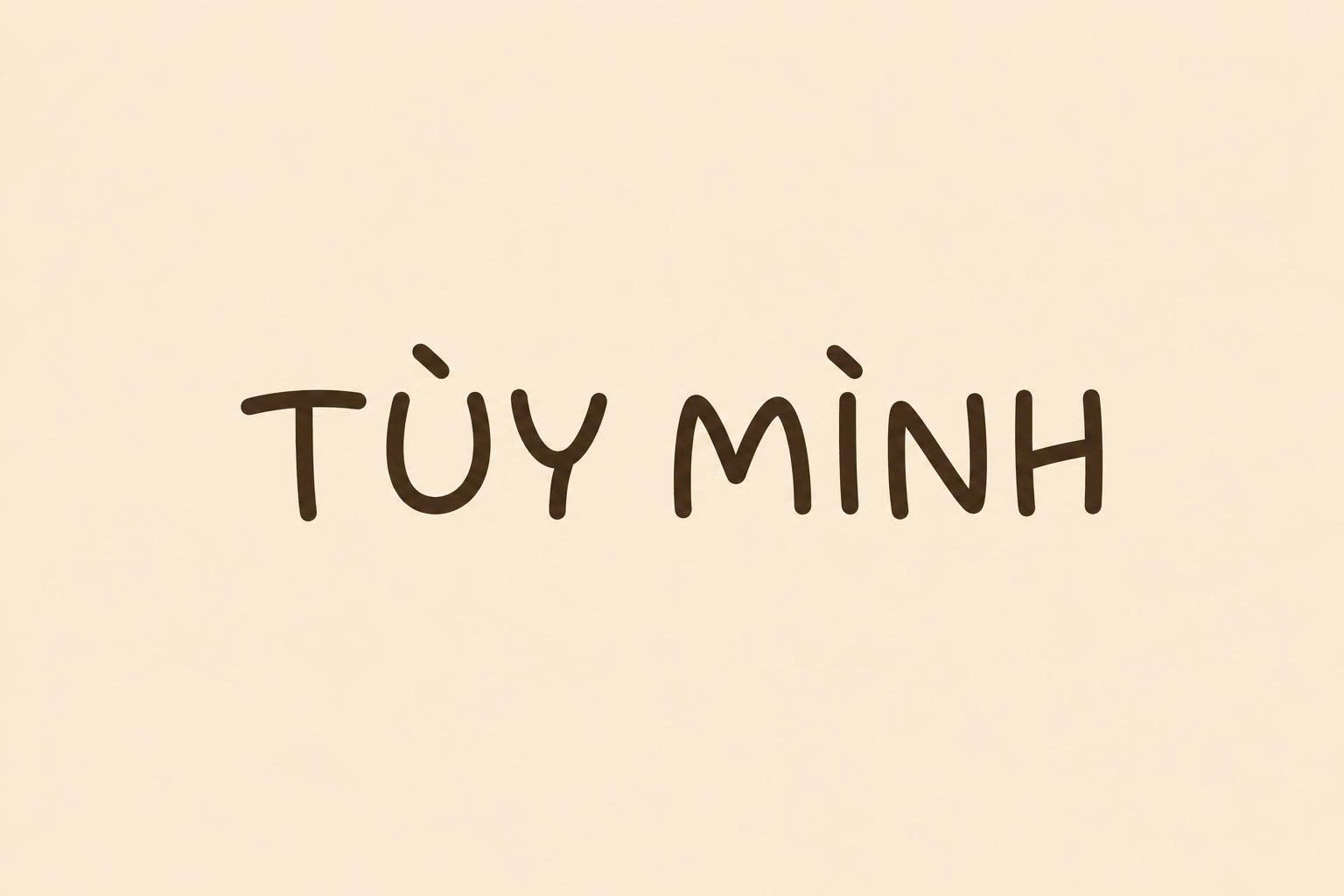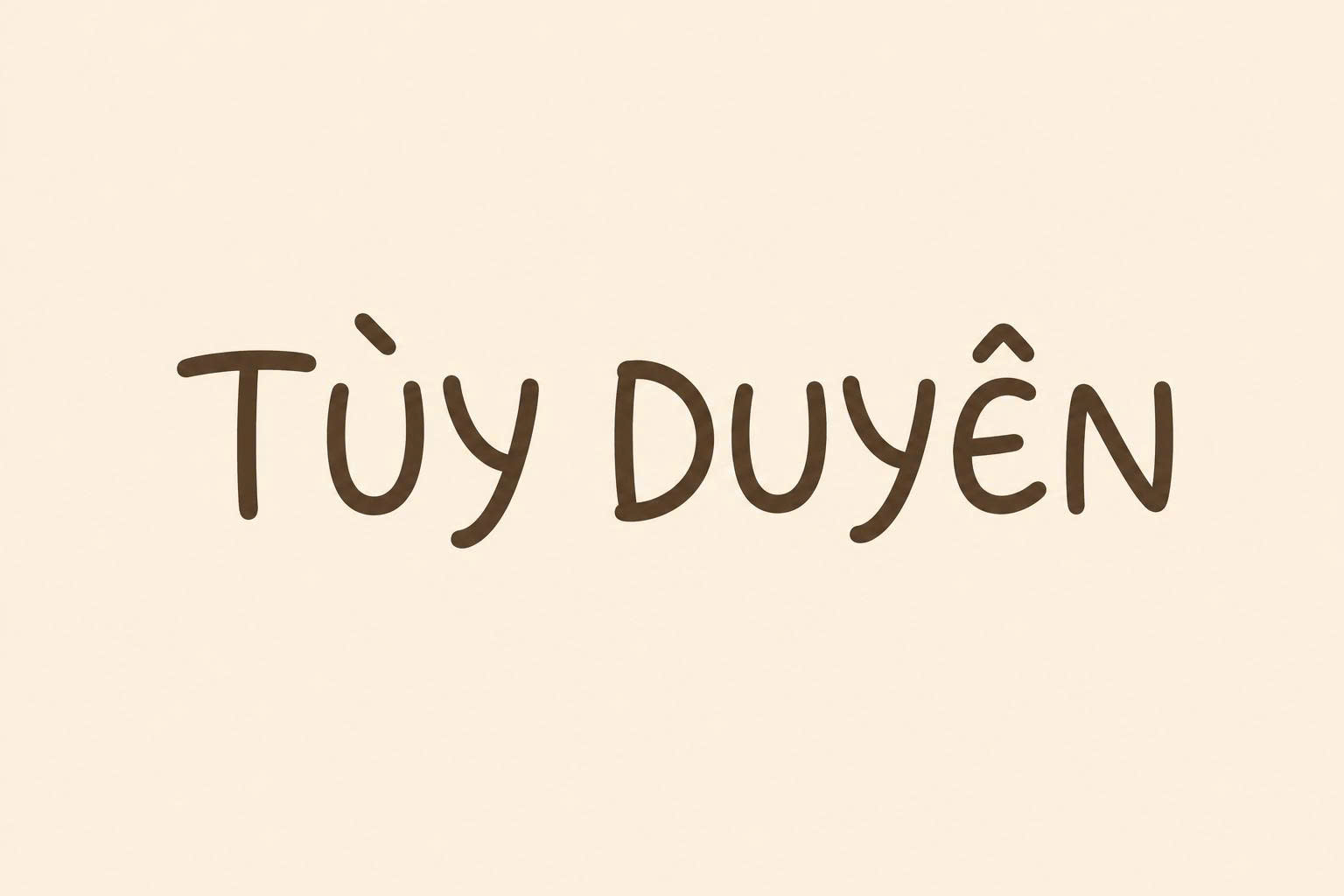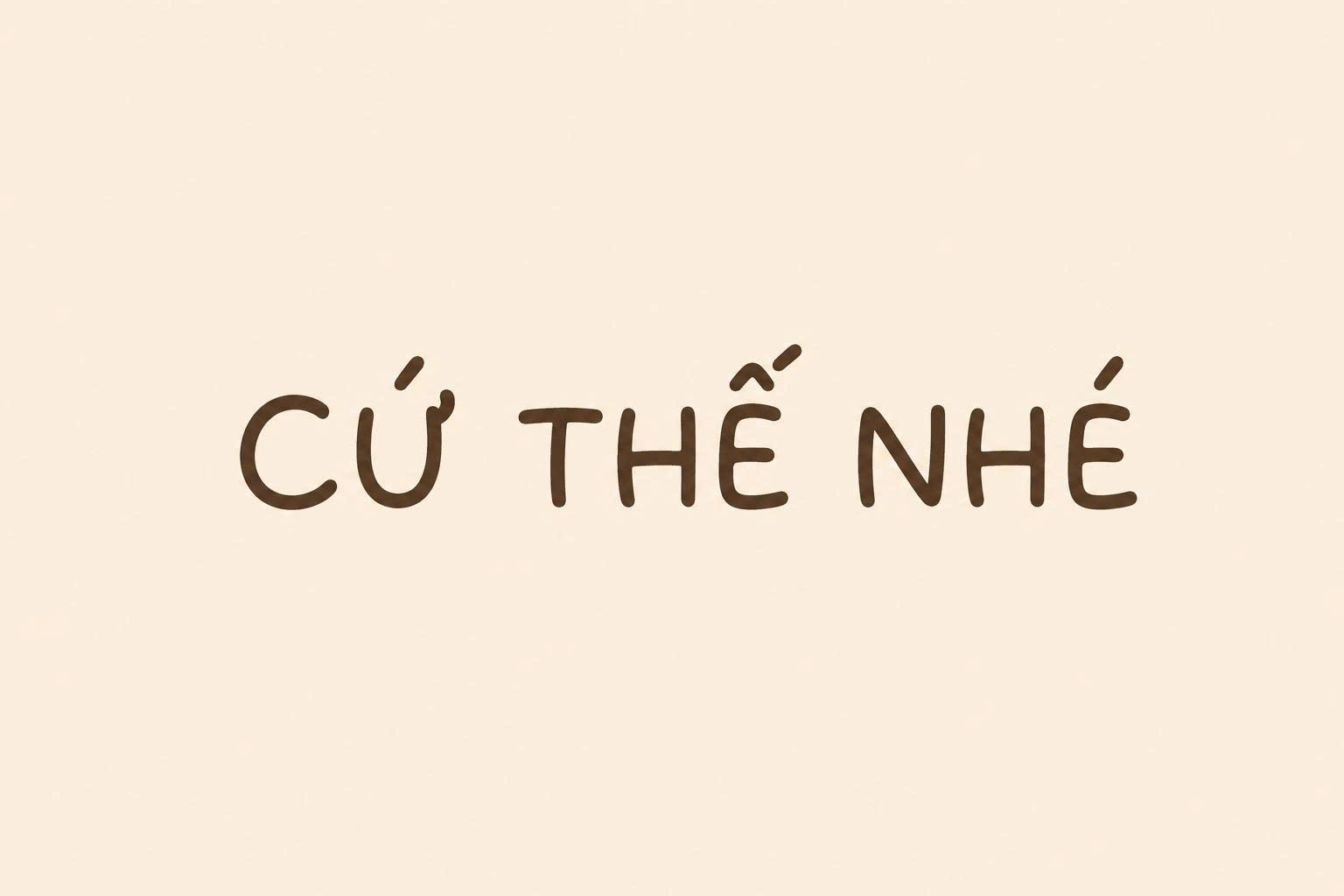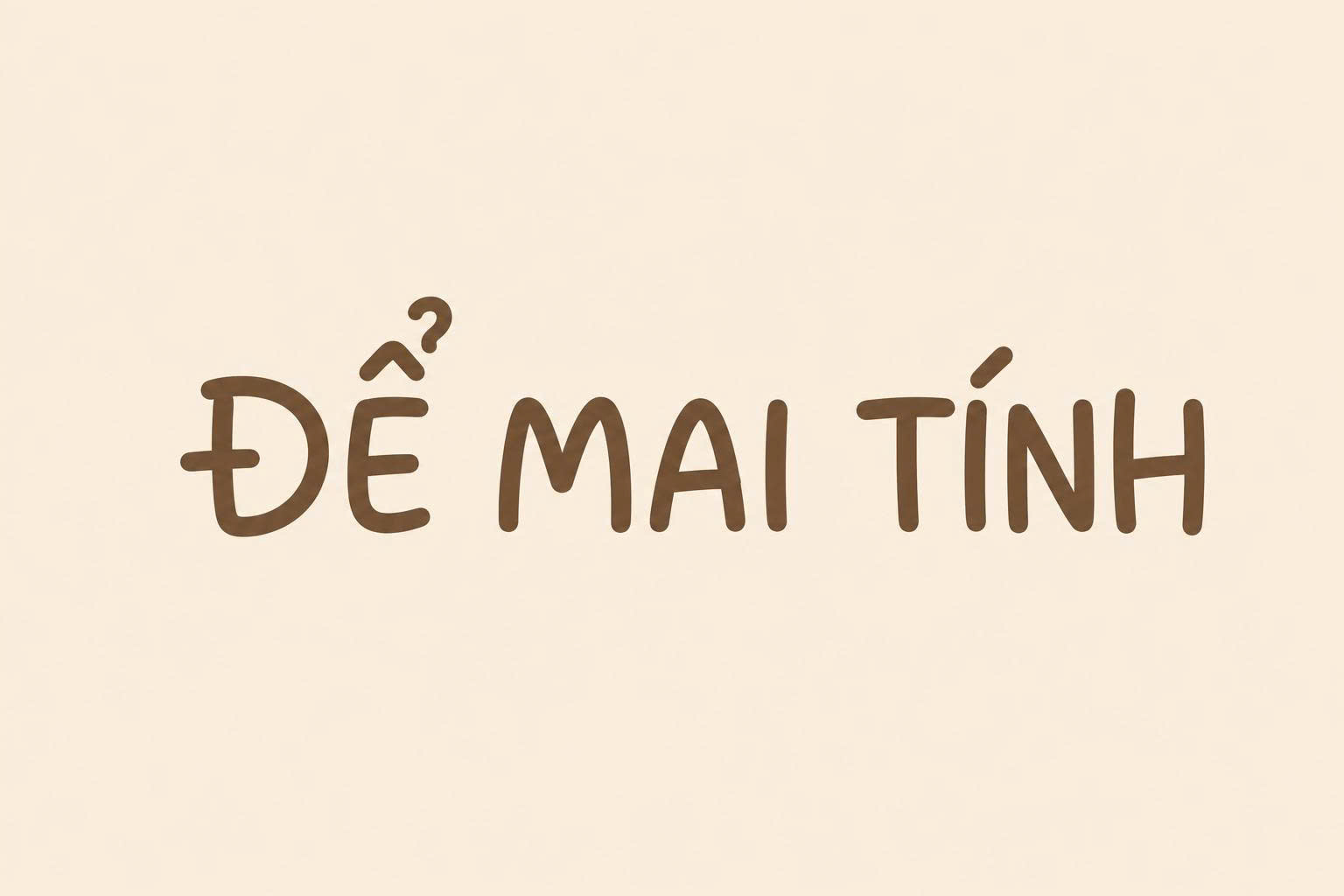
Đặc điểm nổi bật của bộ font Chococooky Việt hóa
Chococooky không chỉ đơn thuần là một kiểu chữ dễ thương; nó sở hữu cấu trúc hình học thông minh giúp duy trì sự cân bằng giữa tính trang trí và độ dễ đọc.
Thiết kế bo tròn mềm mại và dễ mến
Đặc trưng lớn nhất của font Chococooky Việt hóa chính là toàn bộ các góc cạnh và điểm nối đều được bo tròn tuyệt đối. Nét chữ có độ dày đồng nhất, gợi nhắc đến những viên kẹo hoặc những mẩu bánh quy thơm ngon. Chính sự mềm mại này giúp xóa bỏ cảm giác khô cứng của văn bản, tạo ra một không gian thiết kế đầy sự tích cực và vui vẻ.
Độ dễ đọc cao trên nhiều chất liệu in ấn
Mặc dù mang tính cách điệu cao, Chococooky vẫn giữ được cấu trúc ký tự rõ ràng, khoảng hở trong chữ (counter) khá rộng. Điều này giúp font chữ vẫn hiển thị sắc nét ngay cả khi in ở kích thước nhỏ trên tem nhãn decal hay các mặt phụ của hộp giấy. Khi được Việt hóa tại Doozypack.vn, hệ thống dấu thanh được tinh chỉnh mập mạp tương ứng với thân chữ, đảm bảo sự đồng bộ tuyệt đối.
Tại sao designer nên chọn font Chococooky tiếng Việt cho bao bì?
Trong ngành sản xuất và in ấn tại Doozypack.vn, Chococooky thường xuyên xuất hiện trong các đơn hàng dành cho giới trẻ và gia đình nhờ những lợi ích sau:
- Tạo kết nối cảm xúc: Vẻ ngoài “ngon mắt” của font chữ này cực kỳ phù hợp cho bao bì bánh kẹo, snack, giúp kích thích vị giác và thiện cảm của khách hàng.
- Hoàn thiện nội dung tiếng Việt: Việc sử dụng bản Việt hóa chuẩn giúp bạn gõ các tên sản phẩm như “Bánh quy socola” hay “Kẹo dẻo trái cây” một cách chỉn chu, không bị lỗi nhảy font ở các ký tự đặc thù.
- Tính nhận diện cao: Chococooky mang một phong cách rất riêng biệt, giúp bao bì sản phẩm của bạn nổi bật hơn so với các đối thủ sử dụng phông chữ không chân thông thường.
Tư vấn từ chuyên gia in ấn: Do Chococooky có nét chữ khá mập, nếu bạn dự định in trên giấy Kraft có độ thấm mực cao, hãy lưu ý tăng nhẹ khoảng cách giữa các chữ cái (Tracking) để tránh hiện tượng các nét bo tròn bị dính mực vào nhau sau khi in thực tế.
Ứng dụng thực tế của font Chococooky tại Doozypack.vn
Sự vui nhộn của Chococooky mang lại hiệu quả thị giác đặc biệt trên các ấn phẩm tại Doozypack.vn:
- Hộp giấy đựng bánh kẹo: Là lựa chọn số một cho tiêu đề chính trên hộp bánh cookie, kẹo dẻo hoặc sô-cô-la thủ công.
- Tem nhãn dán Sticker: Dùng cho các loại sticker trang trí, tem dán miệng túi bánh tạo phong cách trẻ trung và gần gũi.
- Thiệp và bao thư cho trẻ em: Những dòng chữ chúc mừng bằng font Chococooky in trên giấy mỹ thuật mang lại cảm giác hào hứng cho các bé.
- Túi giấy cho tiệm bánh (Bakery): Tên thương hiệu in bằng font chữ này trên túi giấy trắng hoặc túi Ivory cán màng mờ tạo nên vẻ ngoài vô cùng chuyên nghiệp.
Lưu ý kỹ thuật khi in ấn font chữ nét tròn Chococooky
Sản xuất bao bì sử dụng phông chữ nét tròn và dày như Chococooky đòi hỏi designer cần lưu ý một số vấn đề kỹ thuật tại xưởng in chuyên nghiệp:
- Kiểm soát hiện tượng Dot Gain (Tràn mực): Nét chữ tròn dễ bị mực lan rộng hơn thiết kế gốc làm chữ trông “mập” hơn. Designer nên kiểm tra kỹ các ký tự có khe hẹp như ‘e’, ‘a’ để đảm bảo chúng không bị bết nét trên bản in.
- Lựa chọn màu sắc tươi sáng: Phong cách Chococooky đẹp nhất khi phối với các tông màu Pastel hoặc màu rực rỡ. Tránh dùng các màu quá tối hoặc màu nâu đơn điệu nếu bạn muốn làm nổi bật sự năng động của font.